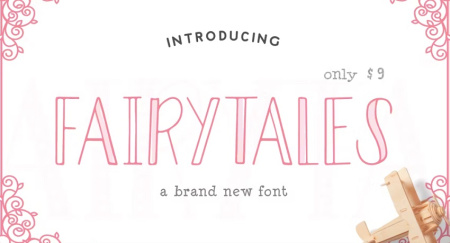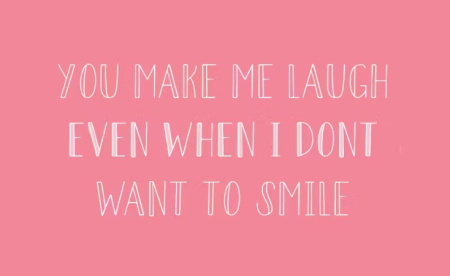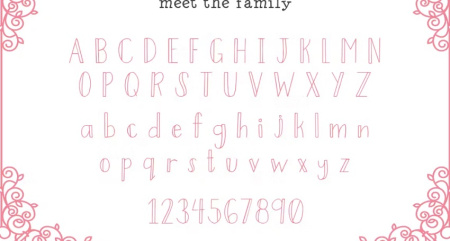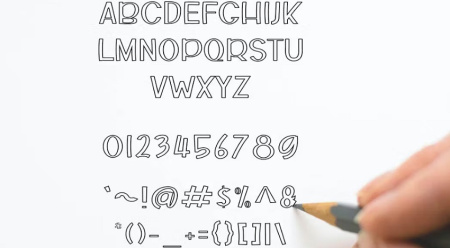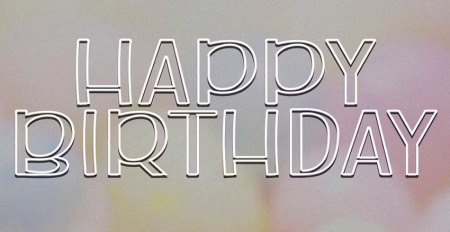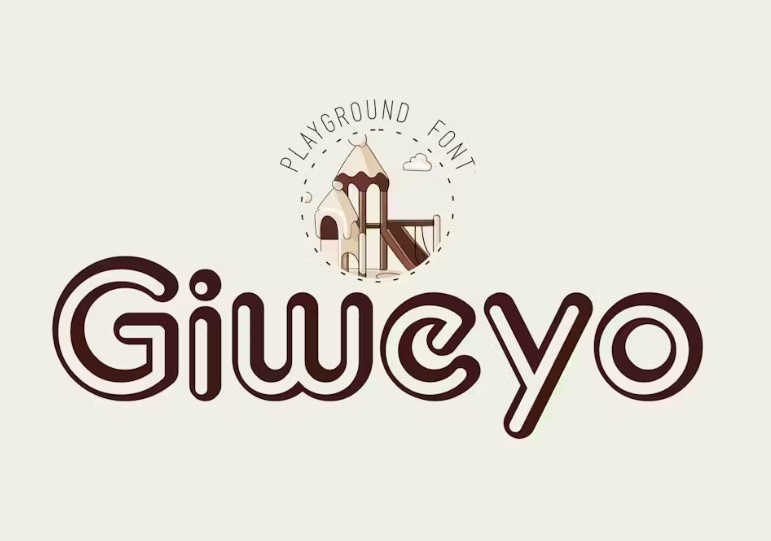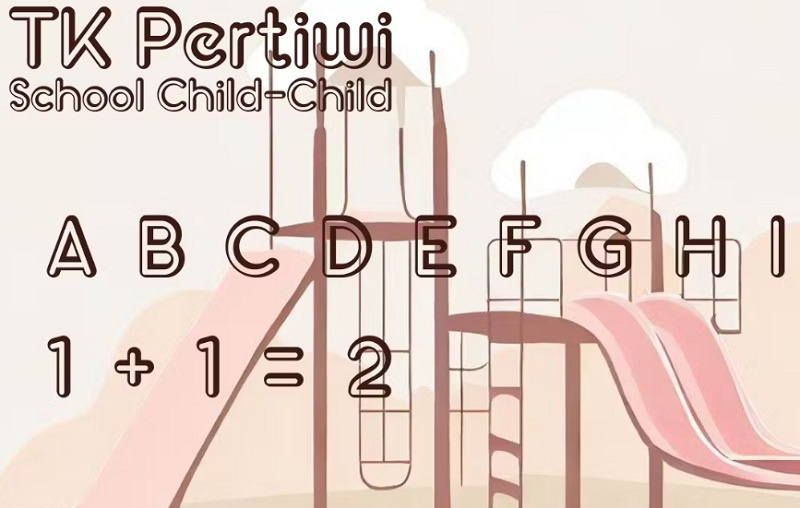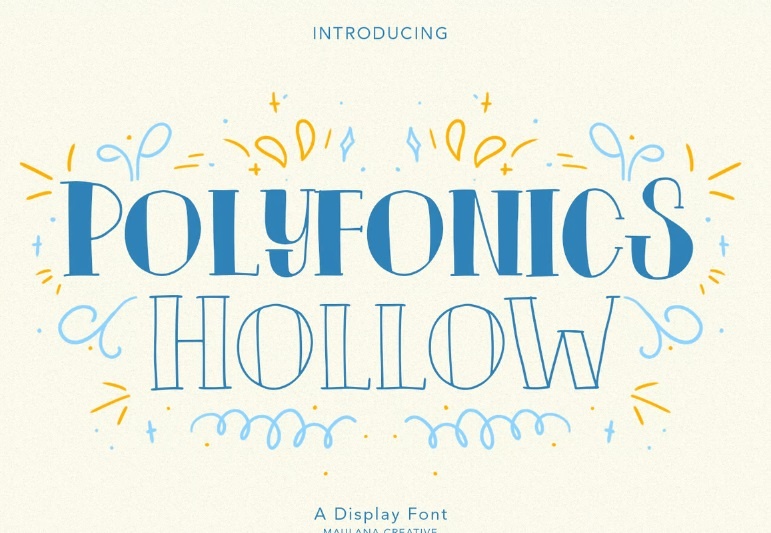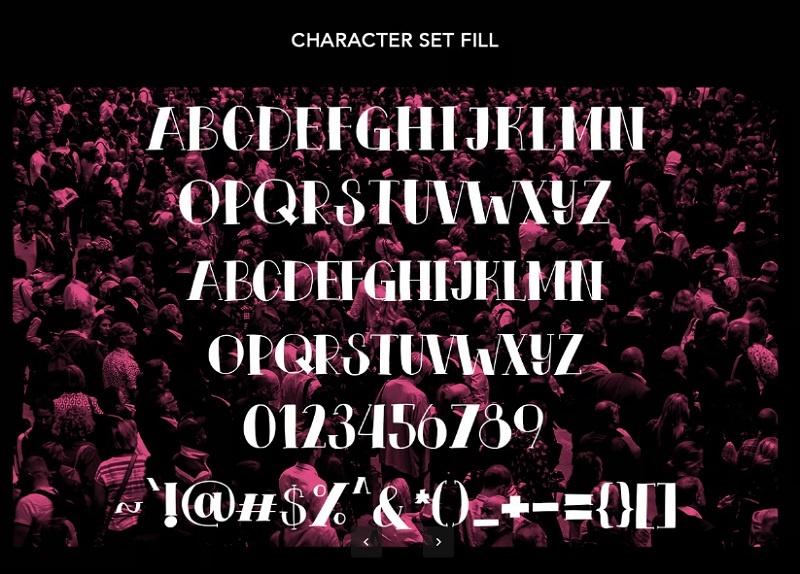
دانلود فونت انگلیسی تو خالی Hollow Font شامل 3 فونت انگلیسی توخالی از جی اف ایکس دانلود می باشد. فونت های زیبا و کاملا جدید به سبک توخالی بسیار مناسب برای طراحی لوگو، مجله، رسانه های اجتماعی، بروشور و بسیاری موارد دیگر نیاز دارید. فونت تو خالی فانتزی مناسب جهت استفاده در طراحی و گرافیک می باشد.
فونت انگلیسی تو خالی ساده
Giweyo یک فونت انگلیسی تو خالی ساده و زیبا است که برای پروژه های گرافیکی و طراحی های مختلف کاربرد دارد. این فونت حروف انگلیسی تو خالی برای کارت تبریک، بسته بندی، لوگو برند، پوستر و ... ایده آل است.
فونت حروف انگلیسی تو خالی
فونت Polyfonics به دلیل ظاهر مدرن و مینیمال، در طراحیهای گرافیکی، لوگو، پوستر و بسیاری از موارد دیگر بسیار محبوب هست. فونت حروف انگلیسی تو خالی از بیش از 100 زبان پشتیبانی می کند و مناسب برای طراحی لوگو، رسانه های اجتماعی، عنوان فیلم، کتاب و ... مناسب است.
دانلود فونت های انگلیسی تو خالی فانتزی Hollow Font